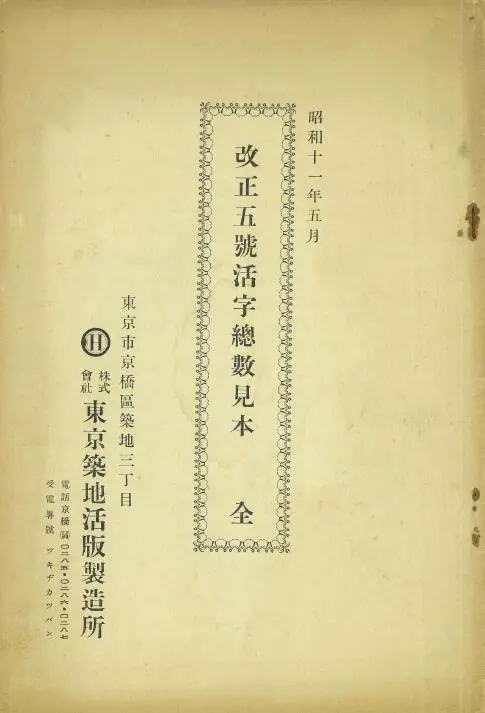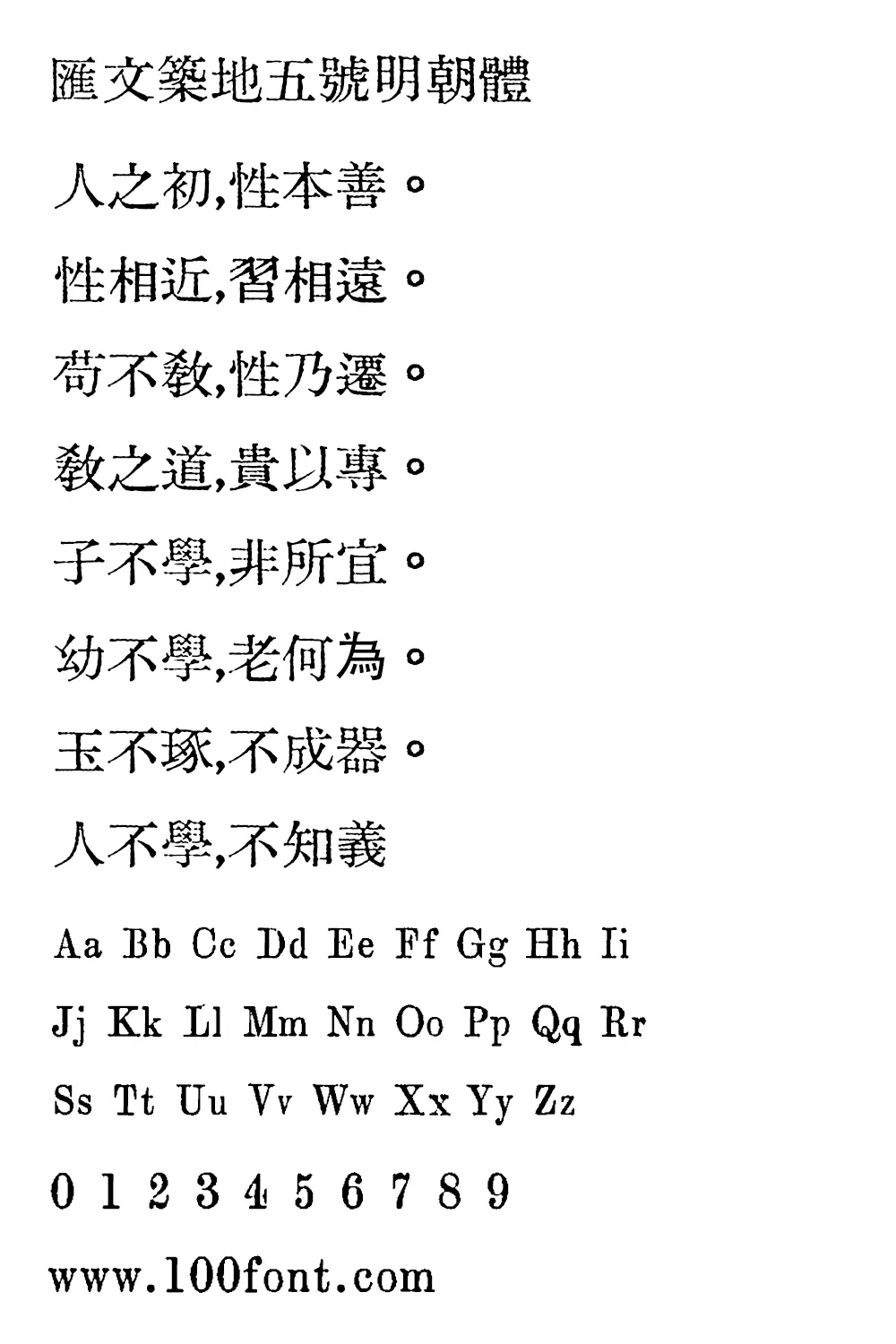
匯文築地五號明朝體是百度“舊字形吧”吧主天王帝廷製作的一款可以免費商用的鉛印風古籍復刻字體,在很久之前吧主就一直有這樣一個想法,做一個民國舊鉛字的掃描字體,但卻不知道怎麼著手去做。主要困難是,要怎樣才能一下收集齊幾乎所有的漢字的字樣?當然不可能買很多很多書籍報紙來一個個找一個個扣。那麼有沒有一本書能一次就包含了所有的漢字在內呢?答案是有的,那就是字典。
但是字典有另外一個問題。首先吧主的主要目的是做一個正文用的鉛字字體,也就是一般常用的五號字體。而用字典很少用到這一字號大小,要不就是字頭的大字,要不就是正文的小字。字頭的大字掃描出來就會像著名的康熙字典體一樣,比較適合作為標題字而非正文排版;正文的小字又太小,而且在這麼多正文里扣出想要的字工作量會比只扣字頭字大得多得多,不太現實。
那還有沒有其他的書能方便地讓我一下就取得儘可能多的、我想要的字號的字呢?這時吧主想到了一本重要的歷史文獻《簡化漢字方案》。於是,在2018年12月,吧主在購買孔夫子舊書網了一系列的漢字改革方案的原始文件回來用於掃描。這些文件包括《漢字簡化方案草案》、《擬定廢除的400個異體字表草案》、《798個漢字簡化表草案整》、《第一批異體字整理表》、《漢字簡化方案》、《簡化字總表》。甚至買了一本《第二次漢字簡化方案草案》,幾乎把所有相關文件拿到了手。
接著就是繁複的掃描、取字、整理分類、錄入工作,然後經過一個春節假期,到2019年3月1日才完成了所有文字改革相關文件的收錄。由於掃描的第一份文件是《文匯報》上面的《漢字簡化方案草案》,又取“收集彙集各方來源的字模來製作成字體”的含義,吧主決定將這一字體命名為《匯文明朝體》。
但是,即使這樣做下來,收錄的字也僅有4000多字,其中缺了很多沒有經過簡化的傳承字。這個程度還沒辦法正常使用。怎麼將剩下的傳承字收錄進來又成了頭痛的問題。這個時候,在外網閒逛的時候發現了這樣一個寶藏,那就是《改正五號活字總數見本全》這本古籍。這本小冊子是日本昭和11年(1936年)東京築地活版製造所出版的,其字形是現在日本明朝體之源流,和當時中國的鉛字字形一樣源自於康熙字典的字形。
這本小冊子收字豐富,非常適合用來補充字庫。於是從3月3日吧主就開始著手整理製作築地五號字體。築地五號據作者所述,是收錄漢字總數八千八百七十八種,但經過吧主的整理,這個數字並不對頭,不管怎麼數都只有8658個字。其中還有117個unicode沒有收錄的字,和26個重複的字。所以共收錄8515個字。然後吧主又順便收錄了所有平假名片假名和241個萬葉假名跟變體假名。然後補了西文字母還有一些圖形符號。所以匯文築地五號明朝體整個字體收錄9262個字符。
吧主本來是計劃用《匯文築地五號明朝體》和他之前製作的《匯文明朝體》合併成一款字體,但是發現這兩款字形風格不太一致!合併後很明顯看得出來是兩種字!這就很難受了。所以吧主現在放棄了這個計劃,而是另外想辦法把《匯文明朝體》的簡繁文字補全。現在吧主也一直在對匯文明朝體進行補全工作,這是一個漫長而艱苦的過程,相信在不久的將來匯文明朝體就會跟大家見面,讓我們一起期待這款字體的面世吧!
現在這款匯文築地五號明朝體算是在製作《匯文明朝體》的過程中衍生副產品,吧主還是無私地放出來免費給大家使用。因為這款字體因為是屬於番外性質的字體,所以古籍中有的字就收錄,沒有的字也不會進行補充。而吧主正在全力製作《匯文明朝體》,而匯文明朝體則會以儘量不缺字為原則進行製作,也就是會包括常用的簡體和繁體字,十分令人期待!!